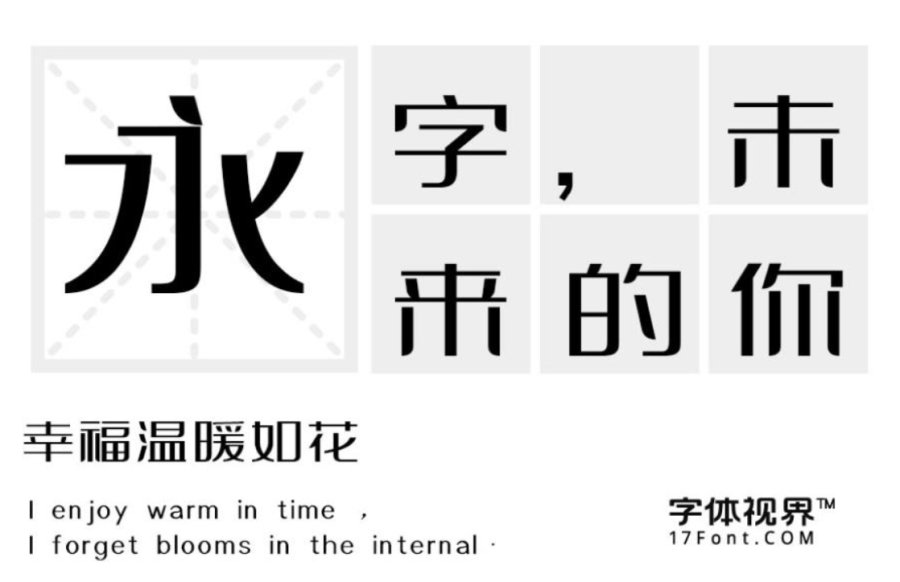
上首秀黑体发布
字体名称:上首秀黑体
字体类别: 黑体字
适用场景:标题、logo、印刷、屏显、动漫、广告、正文
上首秀黑体简介:上首秀黑体,整体特征方正稳重,笔画方中带圆。字体右下角转角处作圆角处理,整体结构刚中带柔,干净洒脱,同时洋溢着成熟、稳重、又不缺泛严谨的风格,适用于户外广告、标准字体搭配、金融医疗、服装、等行业。
上首秀黑体预览图展示: